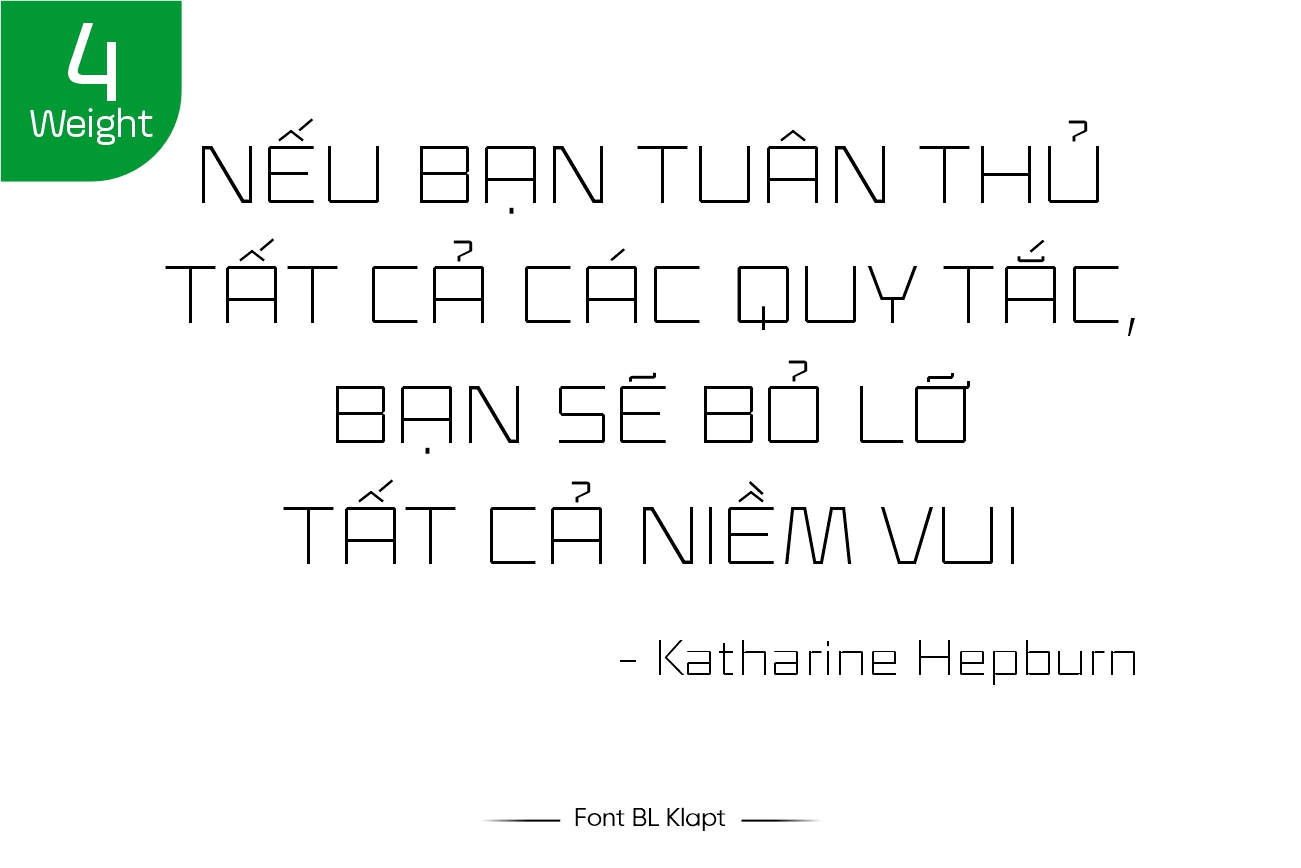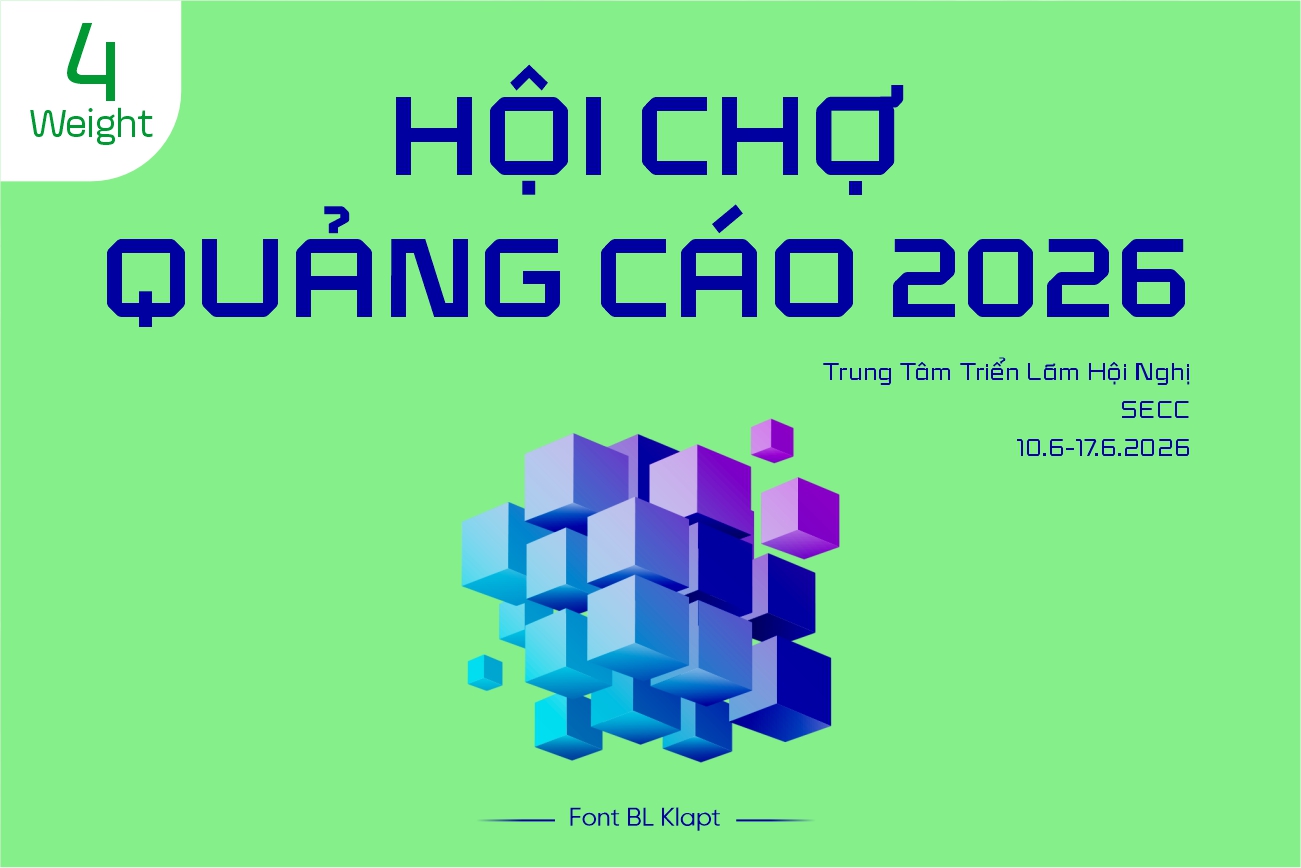
BL Klapt - font sans serif hình học hiện đại
BL Klapt là phiên bản Việt hóa của font chữ Klapt do Vitoria Neves thiết kế, được Team BL tinh chỉnh để đáp ứng đầy đủ nhu cầu sử dụng tiếng Việt trong thiết kế hiện đại. Font gốc Klapt được xây dựng theo tư duy tối giản, chú trọng vào cấu trúc hình học và khả năng ứng dụng linh hoạt. Khi được Việt hóa, BL Klapt vẫn giữ nguyên tinh thần ban đầu, đồng thời được bổ sung hệ thống dấu và ký tự tiếng Việt chuẩn xác, giúp font hoạt động ổn định trong cả in ấn lẫn môi trường số, đặc biệt phù hợp với các dự án thiết kế chuyên nghiệp và mang tính hệ thống.
Về mặt kiểu dáng, BL Klapt là một font sans serif hình học rõ nét, có cấu trúc chặt chẽ nhưng không khô cứng. Điểm đặc biệt của font nằm ở sự cân bằng thị giác: có vẻ ngoài mềm mại bên ngoài và sắc nét bên trong, thể hiện qua các đường bo nhẹ ở góc chữ kết hợp với trục nét dứt khoát. Điều này giúp font vừa thân thiện khi nhìn tổng thể, vừa giữ được sự chính xác và hiện đại trong từng ký tự. Nhờ cách xử lý tinh tế này, BL Klapt tạo cảm giác dễ đọc, sạch sẽ và chuyên nghiệp, phù hợp với nhiều phong cách thiết kế khác nhau.
BL Klapt gồm bốn trọng lượng, cho phép người dùng linh hoạt xây dựng hệ thống chữ rõ ràng và mạch lạc trong cùng một dự án. Từ trọng lượng nhẹ dùng cho nội dung dài, đến trọng lượng đậm dùng cho tiêu đề hoặc điểm nhấn, font vẫn giữ được sự đồng nhất và hài hòa. Chính sự đa dạng này giúp BL Klapt dễ dàng thích nghi với nhiều bối cảnh sử dụng, từ layout tối giản đến bố cục phức tạp, từ ấn phẩm in ấn đến giao diện số. Các khoảng cách chữ và tỷ lệ ký tự được Team BL tinh chỉnh kỹ lưỡng, đảm bảo font luôn ổn định và dễ kiểm soát khi sử dụng tiếng Việt.
Trong ứng dụng thực tế, BL Klapt là lựa chọn lý tưởng cho các thiết kế từ thương hiệu và nhận diện doanh nghiệp đến thiết kế biên tập và thiết kế web. Font đặc biệt phù hợp với logo, hệ thống nhận diện, brochure, website, app UI hoặc các ấn phẩm truyền thông cần sự rõ ràng và hiện đại. Xét về nguồn gốc, Klapt phản ánh rõ tư duy thiết kế đương đại của Vitoria Neves, nơi hình học và cảm xúc thị giác được kết hợp hài hòa. Qua quá trình Việt hóa, Team BL đã nâng cao khả năng ứng dụng của font trong thị trường nội địa, biến BL Klapt thành một font sans serif mạnh mẽ, linh hoạt và đáng tin cậy cho các dự án thiết kế dài hạn.